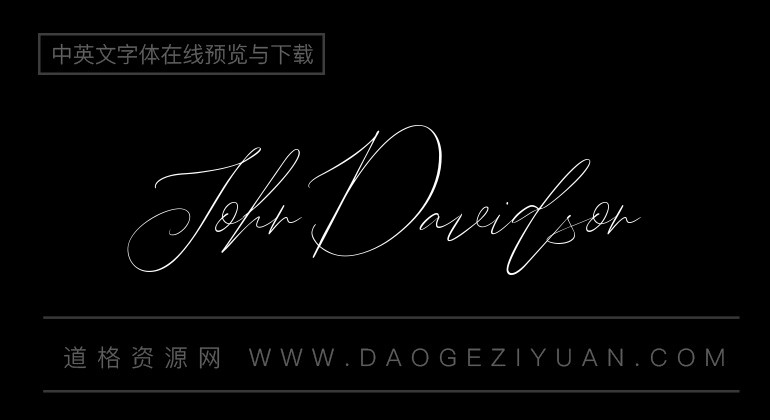
John Davidson 字体是一款古典风格的英文字体,由英国设计师John Davidson于1908年设计。它具有优雅、精致、古典的特点。John Davidson字体的字体设计融合了古典、现代、艺术等多种元素,具有非常独特的风格,使用者可以在文字中体现出优雅的气息。John Davidson字体的可读性也很高,可以让文字更加清晰易懂。内容介绍
John Davidson是一款非常不错的手写艺术字体,具有很好的视觉感,适合于文化类的宣传设计、商业类品牌的广告和产品包装设计以及个性化文字排版等较多场景。